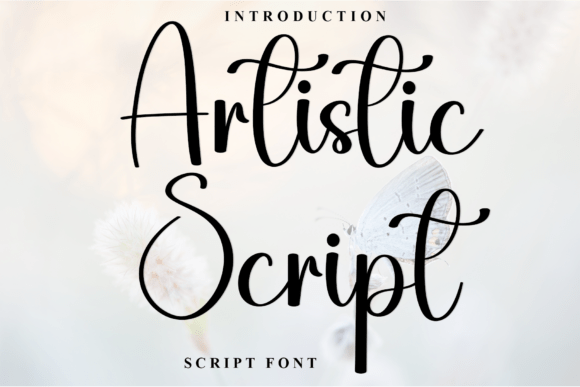
Artistic Script
適切なデザイン要素を見つけるのは難しい場合がありますが、Artistic Scriptは作品を即座に引き立てる優れたコレクションを提供します。
POD(オンデマンド印刷)製品、結婚式の招待状、またはソーシャルメディアのグラフィックを作成している場合でも、Artistic Scriptは理想的です。